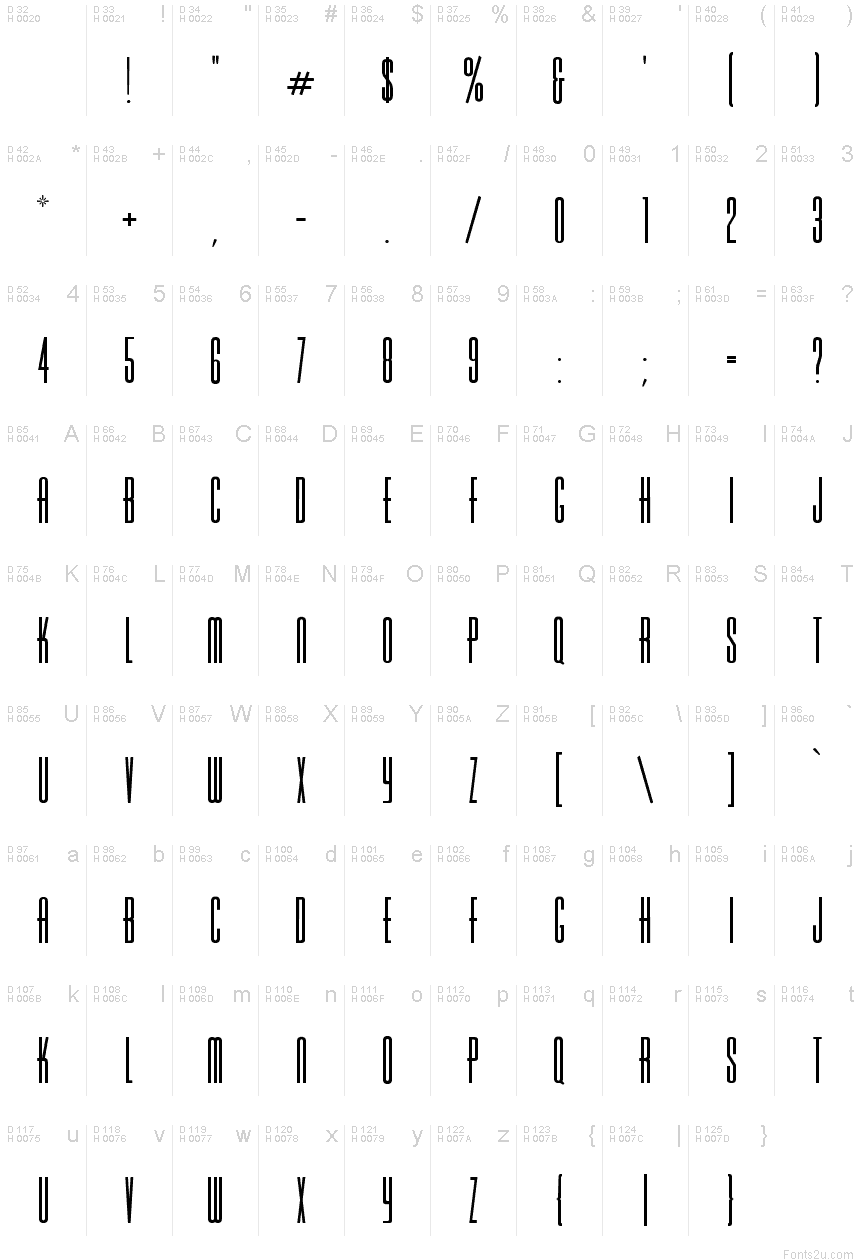
Varicka to darmowy krój pisma typu display w stylu retro, charakteryzujący się niezwykle wąskimi, strzelistymi wielkimi literami. Jego proste kreski i ciasne łuki przywodzą na myśl liternictwo w stylu Art déco oraz vintage szyldy teatralne. Sylwetka fontu jest wyrazista i dramatyczna.
Klub nocny, dom mody lub wydarzenie muzyczne mogłyby wykorzystać Varickę do stworzenia eleganckiej tożsamości inspirowanej minioną epoką, zwłaszcza gdy liternictwo staje się częścią logo lub szyldu. Jego skompresowane proporcje sprawdzają się również w tytułach plakatów i na okładkach albumów, gdzie wysokie formy nawiązują do wieżowców, markiz i innych geometrycznych motywów.
Version 1.000 02/13/2010 Based on 'Varick'. From "Decorative Condensed Alphabets", by Dan Solo, Page 94. It is similar to Red Rooster's Triple Gothic Condensed, but the Solo book's font has different features and shapes.
Varicka
Based on 'Varick'. From "Decorative Condensed Alphabets", by Dan Solo, Page 94. It is similar to Red Rooster's Triple Gothic Condensed, but the Solo book's font has different features.